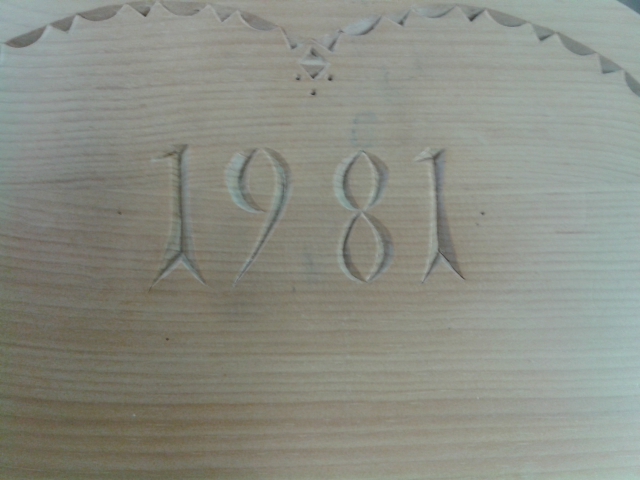
Schrift in Schnitzerei. Wie heisst sie?
Weiss einer wie die Schrift heisst? Gibts so eine Digitale Schrift?post-29194-0-09957400-1413990894_thumb.j
Das ist nicht wirklich eine bestimmte Schrift. Da hat einer sich was von anderen Schnitzereien abgucken wollen und m. E. was falsch verstanden. Die Proportionen der 8 und die Spitzen unten in der 1 scheinen eher verunfallt als gewollt.
Wie heißt sie? Nun, wie heißt der Schnitzer? So würde ich sie vielleicht benennen.
Und dann: Als digitale Schrift? Wohl eher nicht.
Zudem ist es besonders schwer, eine Schriftart allein an Ziffern zu erkennen, da diese oft überhaupt nicht im Stil der Schriftart gestaltet sind, so haben Ziffern von gebrochenen Schriftarten oft recht rund gestaltete Ziffern, die deutlich mehr an eine Antiqua-Schrift erinnern.
Ich würde mich jedenfalls kaum trauen, nur aus den 3 geschnitzten Ziffern die restlichen Figuren der Schrift zu erraten. Das ist eher so eine Art "Handschrift mit dem Schnitzmesser"
Ich habe leider keine Ahnung, wer das ursprünglich erstellt hat.
Gibt es eine ähnliche Schrift?
Dann müsste ich nur noch die Ziffern 1,8 und 9 übernehmen.
Wie ich schon sagte, ein e "ähnliche" Schrift wird es kaum gebenb, solche ähnlichen, etwas simpel und nicht sehr gekonnt geschnitzten Ziffern habe ich auf Bauernmöbeln oder Hausbalken zusammen mit fast jeder Art von Schrift gesehen, also von sinplen Bloickschriften, über geschwungenen oder spitzen Schreibschriften bis hin zu allen möglichen gebrochenen Schriften (Gotisch, Schwabacher und Fraktur), halt alles, was sich irgendwie in Kerbschitz-Technik ausführen lässt
Es währe also ein reines Glücksspiel, hier eine Schrift zu nennen, welche der Schitzer eventuell verwendet hätte. Wahrscxheinlich hat er aber nur einfach diese 3 verschiedenen Ziffern, so gut er halt konnte improvisiert.
Was genau hast du denn vor? Vielleicht kann man dir besser helfen, wenn man mehr weiß ...
Es wären maschinell auf einem weiteren Brett noch weitere Zahlen hinzugefügt worden. Dazu hätte ich einfach die Kontur gebraucht. Die Arbeit wird nun ausswärts gemacht.
Hier würde ich mal behaupen, wenn m an dies dann maschinell, also gefräst ims Holz bringt, wird das Ergebnis auf alle Fälle andera aussehen,  als wenn dies wie in der Vorlage mit dem Schgnitzmesser gemacht wird. egal wie nah der Font der Vorlage auch kommt.
Wenn  es der Vorlage sehr nah kommen soll, würde ich die handwerkliche Lösung vorziehen.